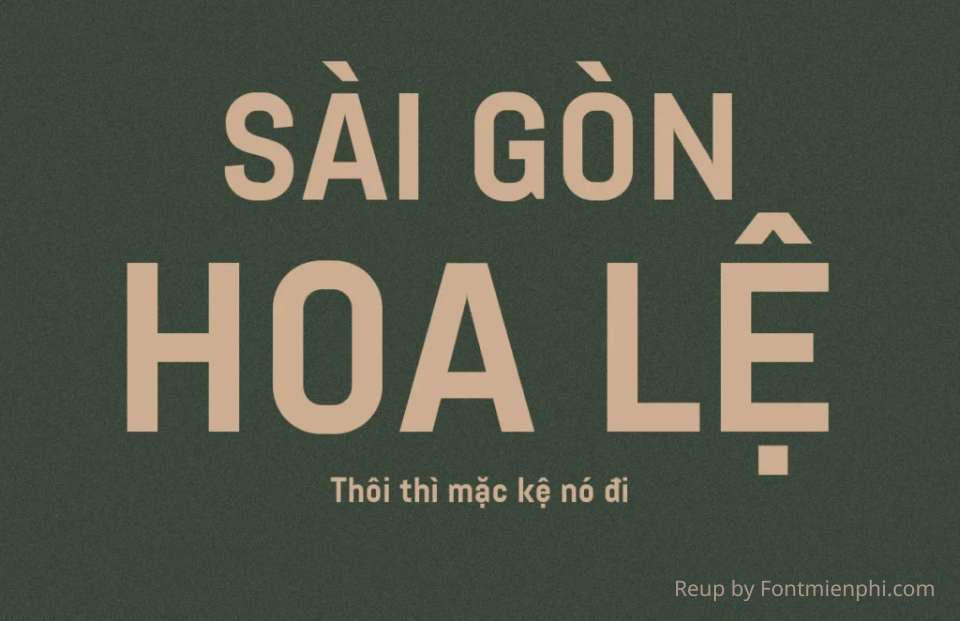
Font VL Abel Pro Bold Việt Hóa – Lựa Chọn Đột Phá Cho Tiêu Đề Thiết Kế
Mang phong cách Sans Serif hiện đại, VL Abel Pro Bold là phiên bản chữ không chân nét đậm sinh ra để làm chủ mọi ánh nhìn. Font mang lại cảm giác mạnh mẽ, rõ ràng nhưng không hề thô cứng, giúp các đoạn tiêu đề trở nên cực kỳ thu hút và gọn gàng.
Những Điểm Sáng Giá Nhất Của VL Abel Pro Bold
Tối ưu không gian hiển thị: Dáng chữ được thiết kế hơi hẹp (condensed) kết hợp cùng chiều cao ký tự lớn. Nhờ đó, font trông rất cao ráo, dễ đọc và loại bỏ hoàn toàn cảm giác nặng nề khi thiết kế ở kích thước (size) lớn.
Việt hóa hoàn chỉnh: Được thực hiện bởi Font Việt Linh, phông chữ cam kết hiển thị chuẩn xác mọi dấu câu tiếng Việt, nét chữ đồng đều, đáp ứng hoàn hảo từ thiết kế online cho đến in ấn chuyên nghiệp.
Ứng dụng đa năng: Đây là “vũ khí” tuyệt vời cho các vị trí trọng tâm như Headline, tiêu đề Website, Banner quảng cáo, Poster hay Thumbnail.
Mẹo Kết Hợp Chữ (Font Pairing) Chuyên Nghiệp
Để tạo ra một bố cục rành mạch và cuốn hút, hãy sử dụng VL Abel Pro Bold cho phần tiêu đề chính, và kết hợp cùng phiên bản Regular (hoặc các font Sans Serif nét mảnh khác) cho phần nội dung mô tả. Sự tương phản rõ rệt về độ dày mỏng này sẽ giúp thiết kế của bạn trở nên chuyên nghiệp, hiện đại và thân thiện với mắt người đọc hơn rất nhiều.